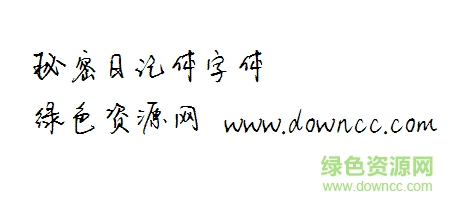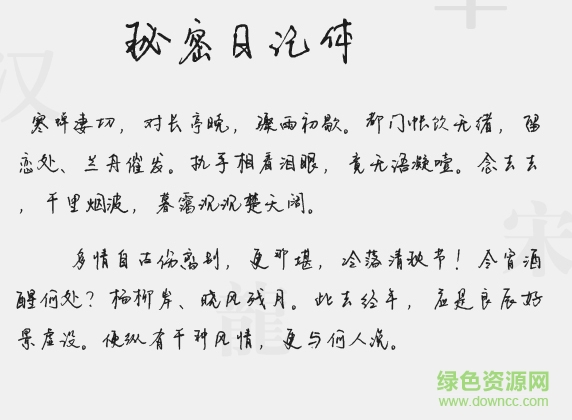
秘密日記體字體頗有一副手寫草書體的氣概,該字體筆畫隨心所欲行如流水,字里行間能透露出作家的思緒情感,非常好看,歡迎到綠色資源網(wǎng)下載安裝!
秘密日記體是一款適合鋼筆書法書寫的字體,該字體的誕生,要經(jīng)過字體設(shè)計師的創(chuàng)意設(shè)計、字體制作人員一筆一劃的制作、修改,技術(shù)開發(fā)人員對字符進行編碼、添加程序指令、裝庫、開發(fā)安裝程序,測試人員對字庫進行校對、軟件測試、兼容性測試,生產(chǎn)部門對字庫進行最終產(chǎn)品化和包裝上市!